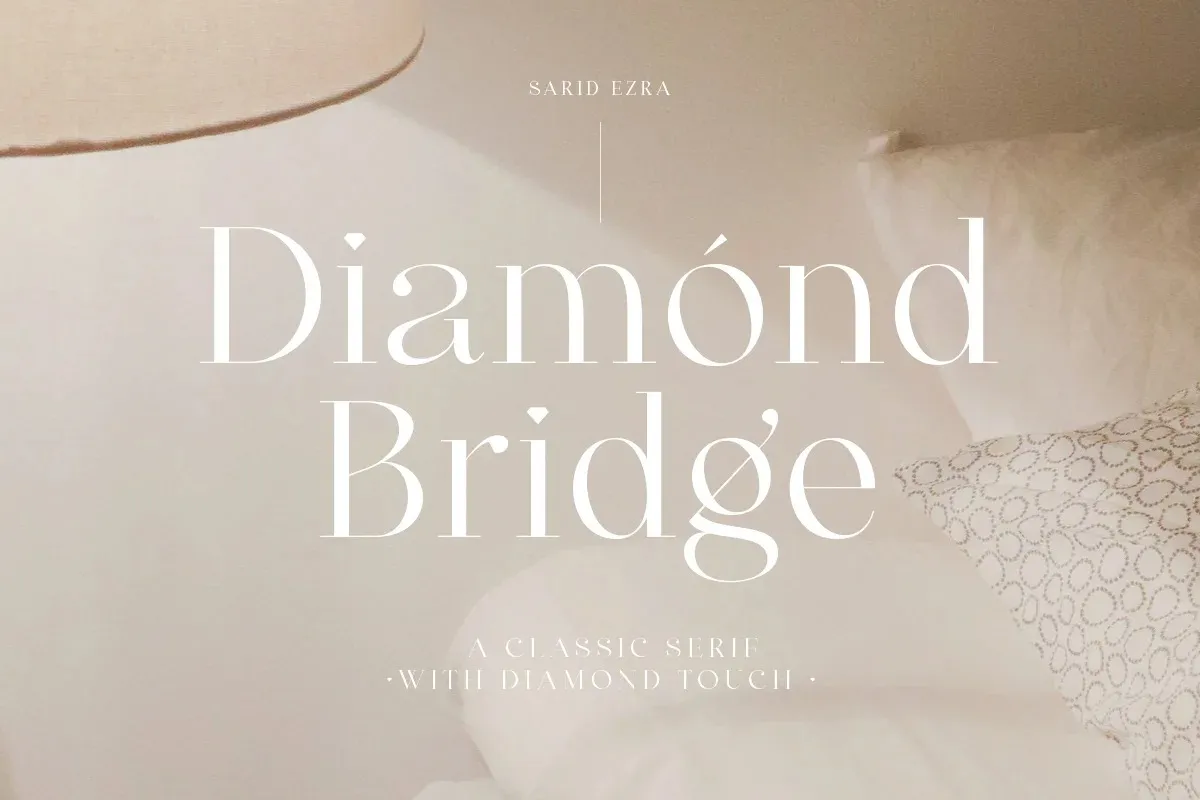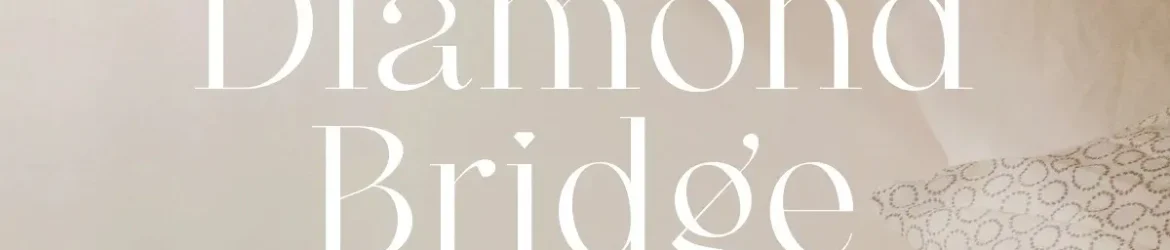
A Diamond Bridge Font é uma elegante tipografia serifada criada pelo designer Sarid Ezra. Ela oferece um toque refinado e se destaca por sua facilidade de uso, tornando-a perfeita para criar designs formais. Esta fonte é ideal tanto para cartões de casamento quanto para identidades corporativas personificadas. Suportando múltiplas línguas, ela está pronta para usar (PUA Encoded), facilitando sua integração em qualquer projeto visual. Com a Diamond Bridge Font, você pode criar designs singulares e sofisticados que transmitirão um alto nível de qualidade e estilo. Seja você ou seu cliente, essa fonte será uma escolha inteligente para expressar sua marca de maneira única.